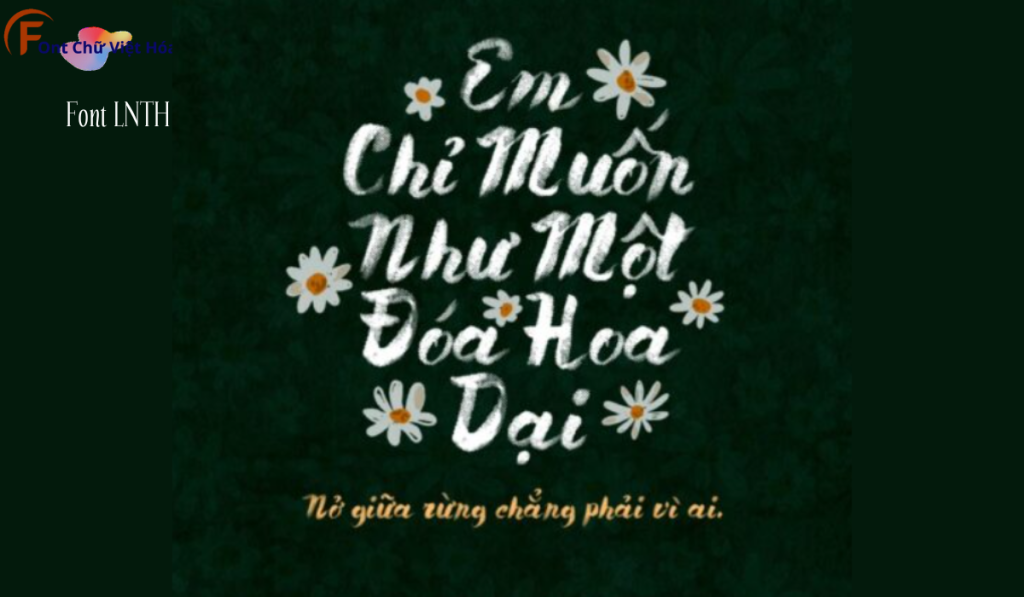
Font LNTH Pale Blue Eyes Việt Hóa
Tác giả: LNTH Pale Blue Eyes
Bộ Font: LNTH
Phân loại: Cá tính, độc đáo
Font LNTH Pale Blue Eyes Việt Hóa là một font chữ nhẹ nhàng, thuộc bộ LNTH, với thiết kế thanh thoát và tinh tế. Phong cách của font này phù hợp với các dự án thiết kế cần sự nhẹ nhàng và tinh tế, như thiệp mời, bìa sách, hoặc logo. Font LNTH Pale Blue Eyes Việt Hóa mang đến sự nhẹ nhàng và dễ nhận diện, ứng dụng trong các lĩnh vực sáng tạo. Đặc điểm hình dạng của font bao gồm các đường nét thanh mảnh và tinh tế, giúp tăng tính thẩm mỹ và sự chú ý. Việc Việt hóa font giúp người dùng dễ dàng sử dụng trong các thiết kế tiếng Việt, mang lại sự tiện lợi và linh hoạt.